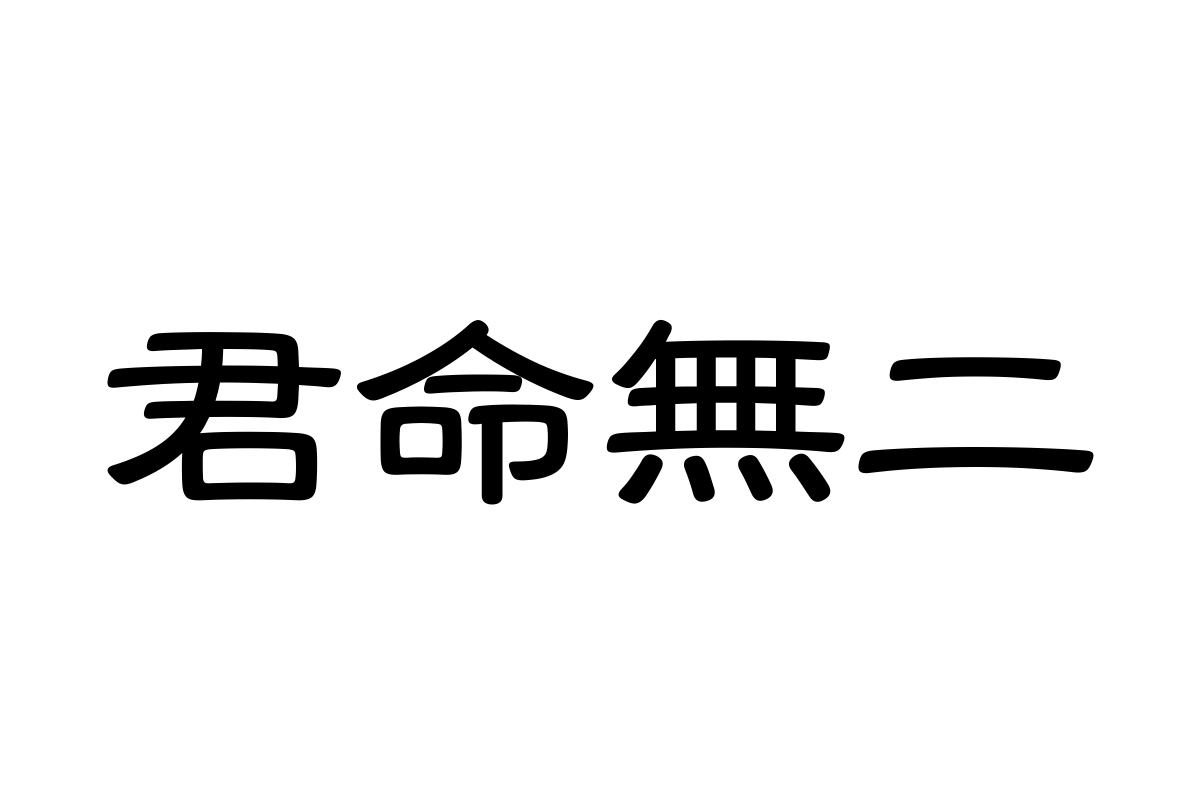
汉仪玉筋隶65繁体是一款具有独特风格的字体,它采用了传统的汉字书写风格,将楷书的笔画和结构进行了简化和优化。这款字体的特点是笔画流畅、结构紧凑,适合用于各种印刷品和设计作品。
在设计上,汉仪玉筋隶65繁体注重细节的处理,每个字的笔画都经过精心雕琢,使得整体看起来更加美观大方。同时,这款字体也具有一定的可读性,无论是阅读还是书写都非常舒适。
总的来说,汉仪玉筋隶65繁体是一款非常实用的字体,无论是在印刷品还是设计作品中都能展现出其独特的魅力。